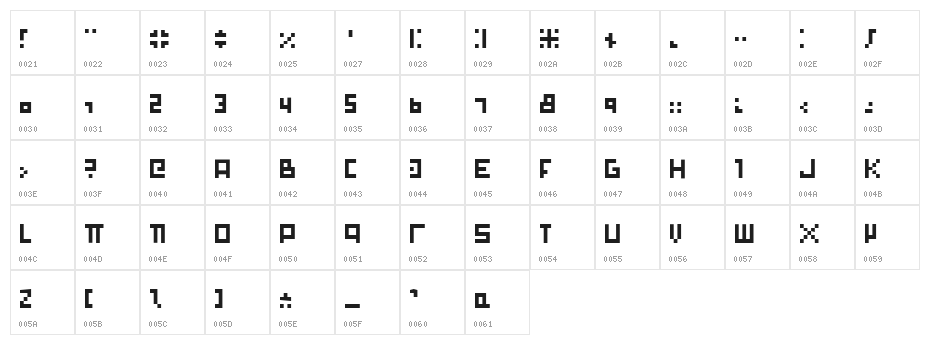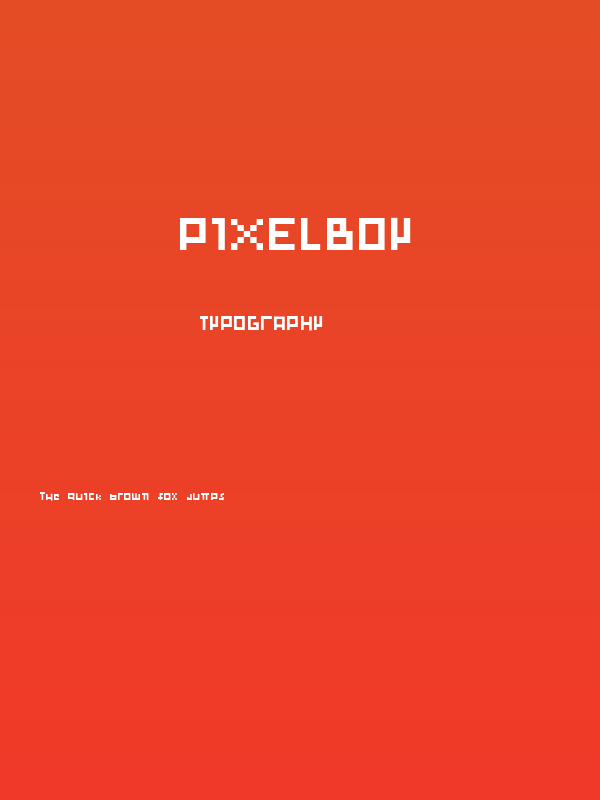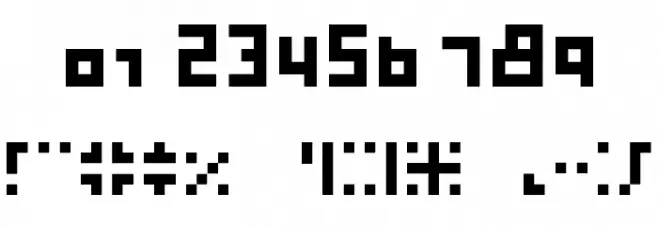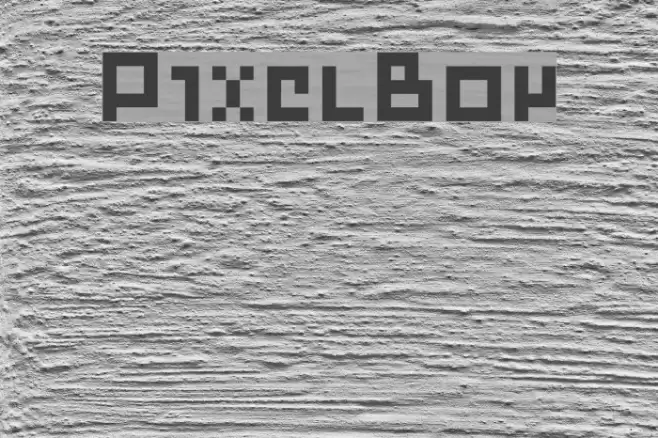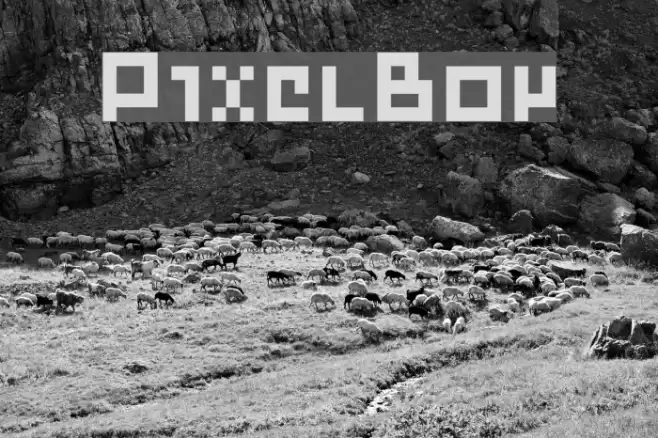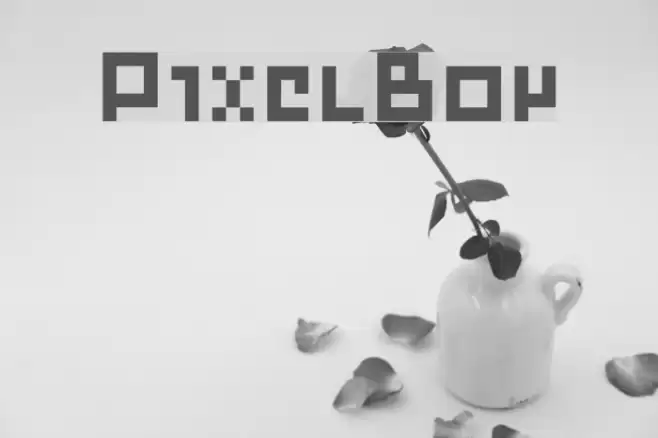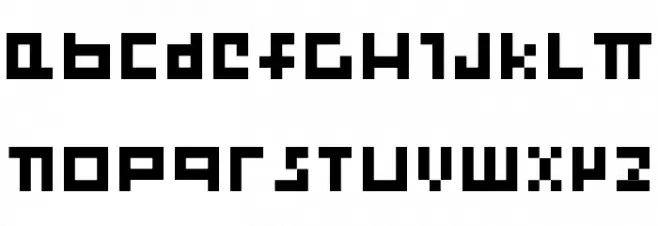
PixelBoy Font
| Caz de utilizare | Headlines, Logos, Digital Art |
| Proiecte propuse | Ideal for video game design, retro-themed posters, digital art projects, and any creative work that seeks to evoke nostalgia for early computer graphics. |